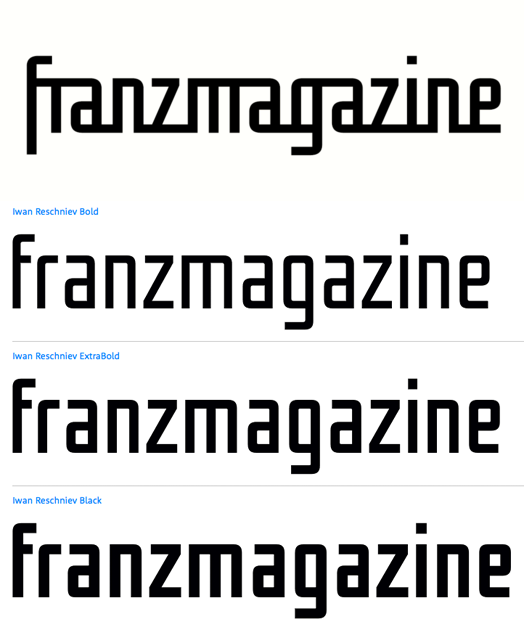
Franzmagazine ... (Iwan Reschniev?)
Bin grad über dieses Logo gestolpert:
und frage mich ob das (meine) Iwan Reschniev ist oder etwas sehr ähnliches gibt (bei dieser Schrift ja möglich)? Ich bin grad von dieser "Script"-Variante sehr angetan :rockon:
Oben: Logo
Unten: Screenshots von myfonts
Ich würde sagen, da hat einer dem Iwan neue Kleider angezogen.  :-D
Lass Dich doch davon inspirieren zu einer Script-Variante – schick wäre natürlich auch noch eine Slab und am liebsten auch Kursive!  :cheer: